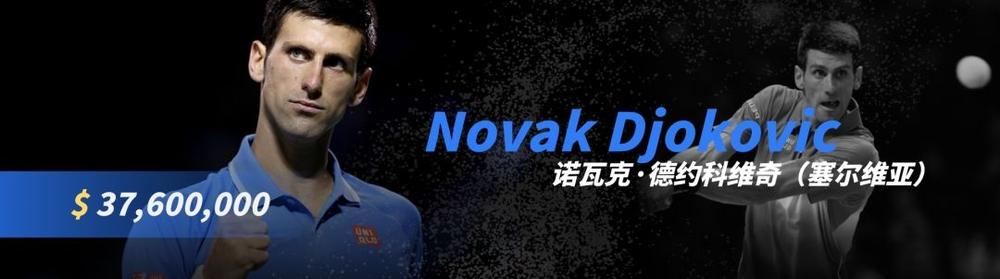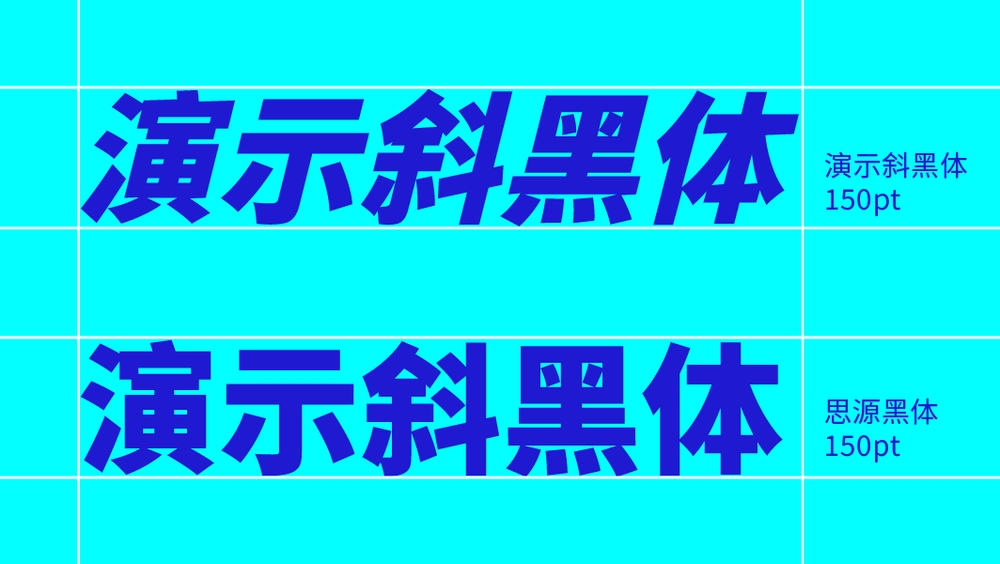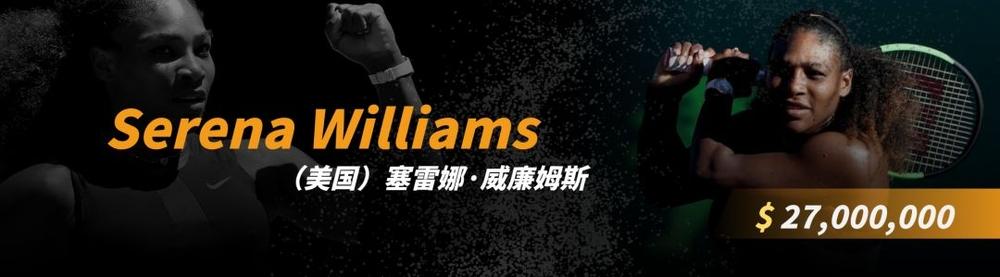
演示斜黑体(Source-KeynoteartHans)是基于思源黑体的改造,将字形整体向右倾斜形成的一种全新的倾斜式无衬线黑体。看“演示”两个字就知道是由 Keynonte 研究所出品的“演示系列”,主要是为了解决中文字体不能在 Keynote 中切斜的问题。
中文斜体是源于西文的 Italitic,而通过 PowerPoint 的倾斜得到的是一种伪斜体,并不能得到字体届的认可,所以 Keynote 里面没有斜体。正如普通字体的加粗不一定美观,所以在 Keynote 里面可以选择字重。PowerPoint 单独将每种字重默认为一种字体,比如 Windows 自带的黑体加粗后就很难看、思源黑体倾斜角度也太大不好看,而演示斜黑体正好解决这一问题。
演示斜黑体总共收录了30888个字体,定位为标题字,适用于品牌LOGO、Slogan字体,电商双11、618海报主图标题,在PPT幻灯片中配合动画效果也很不错。因是在思源黑体的基础上改造而来,所以也属于SIL开源字体授权,可以免费商用但禁止售卖。